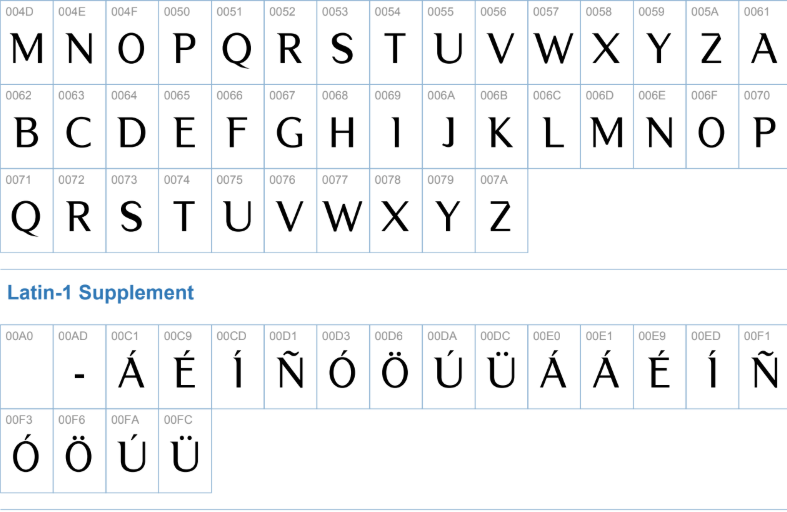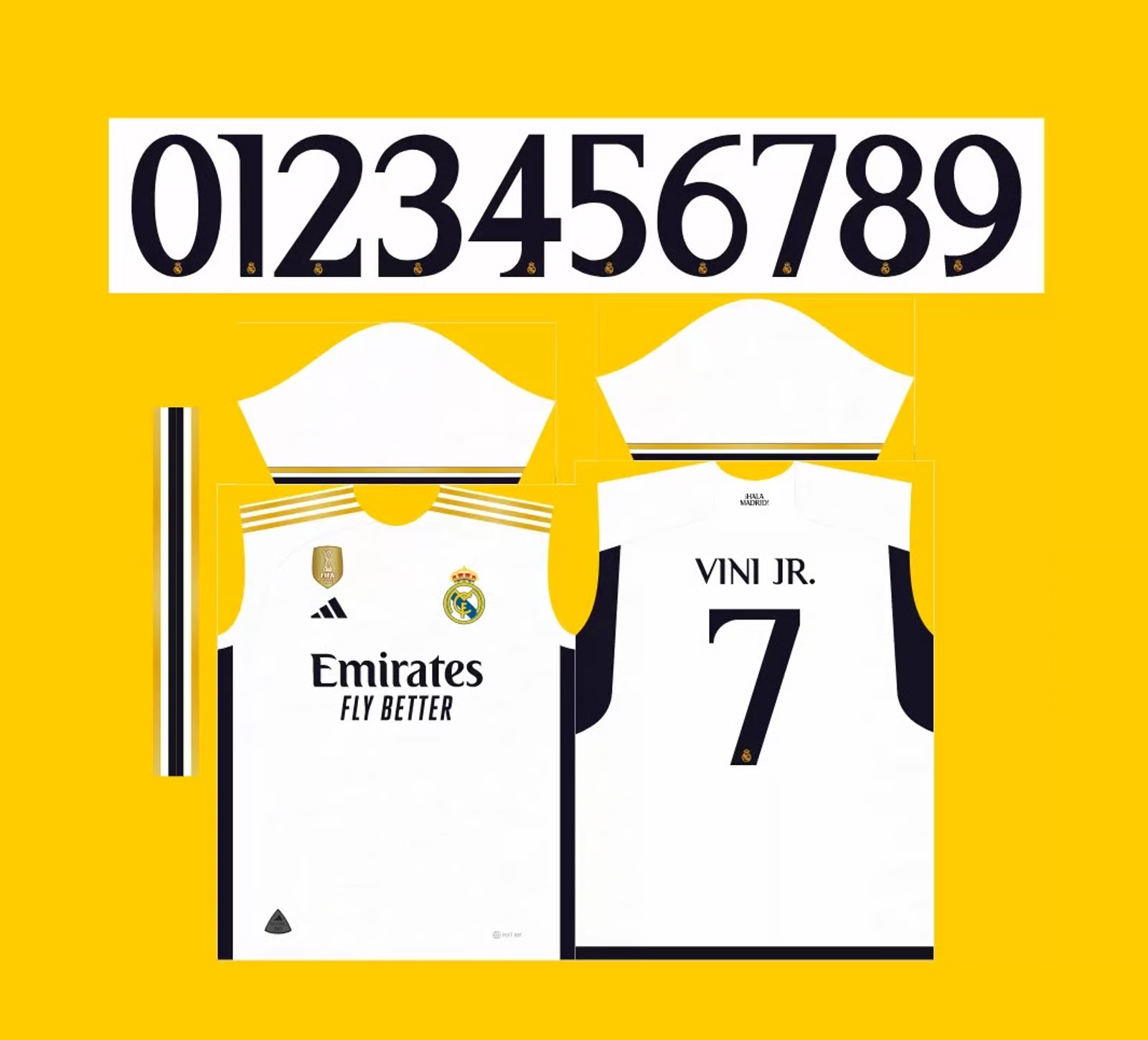
A temporada 2023-2024 do Real Madrid não é marcada apenas por grandes jogos, mas também por um visual que combina tradição e modernidade. A Adidas, mais uma vez, acertou em cheio no design dos uniformes, e um componente crucial dessa identidade é a tipografia exclusiva usada nas costas dos jogadores.
Seja para personalizar um material gráfico, criar um mockup para redes sociais ou simplesmente estudar o design system dos “Galácticos”, ter a fonte correta é essencial. Esta é a fonte que estampa os nomes de craques como Vini Jr., Bellingham e Rodrygo nos gramados da La Liga e da Champions League.
Detalhes Técnicos da Fonte
- Nome da Fonte: Real Madrid 2023-2024 (Variação da tipografia oficial da Adidas)
O Estilo Visual: Elegância e Modernidade
A Adidas desenvolveu para o Real Madrid nesta temporada uma fonte que equilibra perfeitamente robustez e elegância. Ela possui um design sans-serif (sem serifa) com linhas limpas e cantos levemente arredondados, garantindo excelente legibilidade em alta velocidade, seja na TV ou no estádio.
O que a torna única são os cortes sutis e a largura levemente condensada, que transmitem uma sensação de velocidade, precisão e sofisticação. É uma fonte moderna, que se alinha à imagem global do Real Madrid como um clube de vanguarda, mas sem perder a seriedade que o escudo exige.